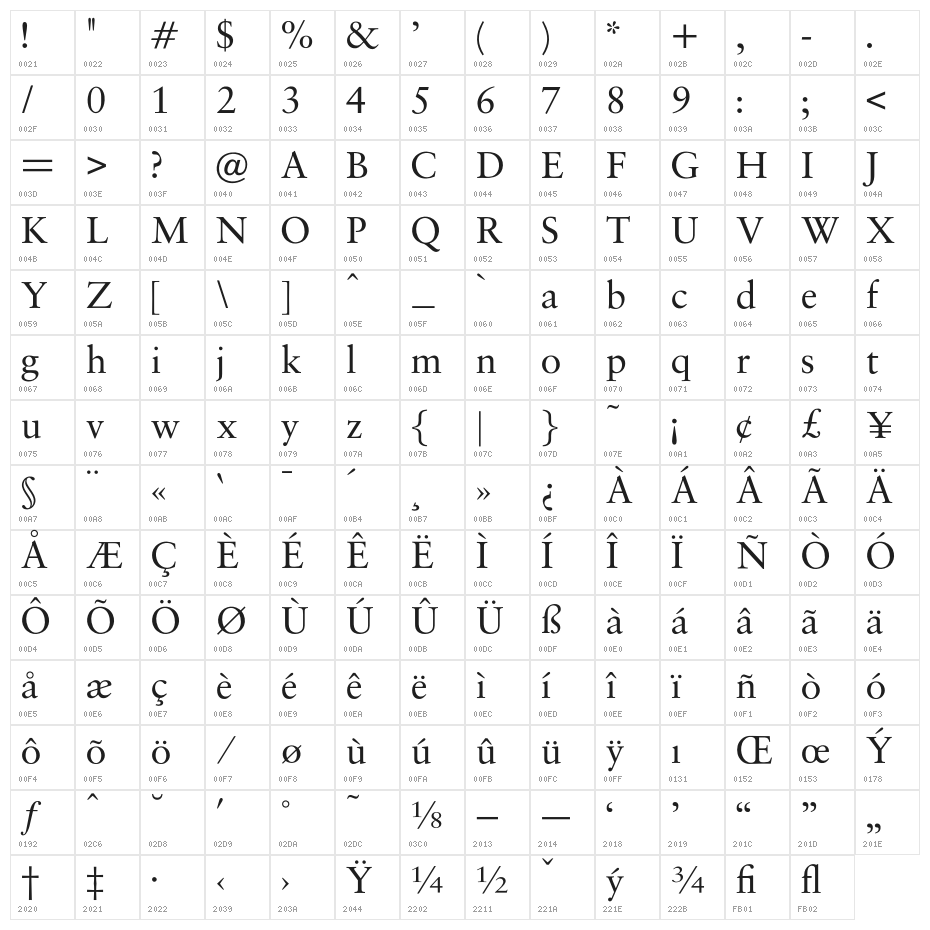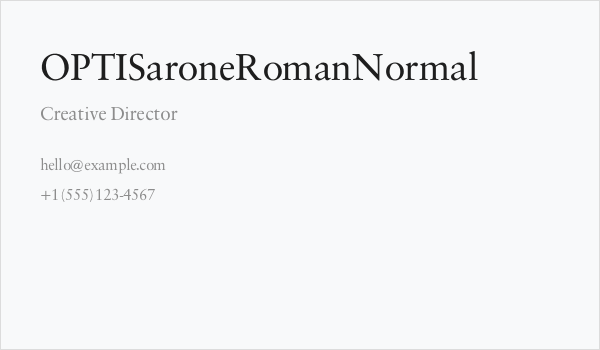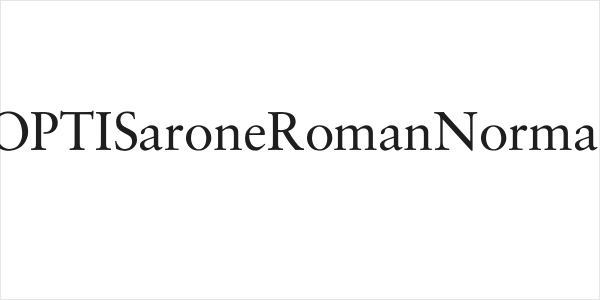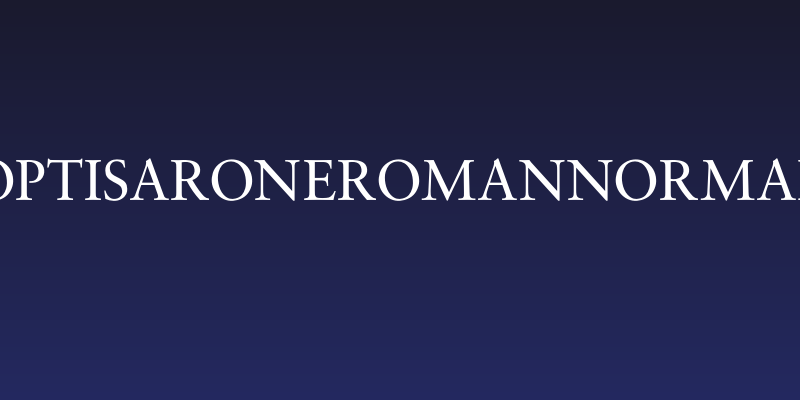
OPTISaroneRomanNormal Font
| Proiecte propuse | Ideal for editorial design, book covers, formal invitations, and branding projects that require a touch of elegance. |